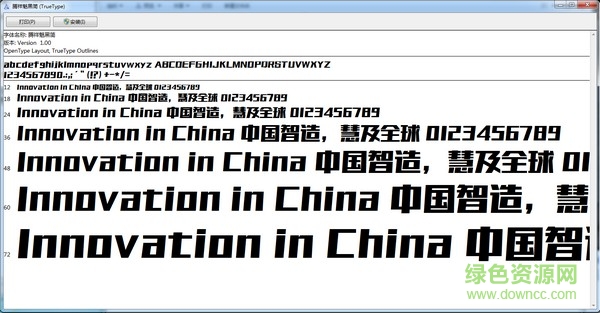
tensentype meiheij字體又叫騰祥魅黑簡(jiǎn)字體,粗而不重,布局精妙,大氣美觀,可以廣泛應(yīng)用于排版影視、包裝設(shè)計(jì)、平面設(shè)計(jì)等多個(gè)領(lǐng)域,需要的朋友快來(lái)下載吧!
魅黑是一款富于變化的美術(shù)類(lèi)黑體。魅黑是在潮黑的風(fēng)格特征基礎(chǔ)上設(shè)計(jì)而成。字形結(jié)構(gòu)扁方,橫豎筆畫(huà)粗細(xì)比例適度、所有豎筆及撇捺筆畫(huà)均呈右傾斜式,為了空間的布局,每個(gè)筆畫(huà)的傾斜角度由左至右形成梯度,使整個(gè)字看起來(lái)呈梯形,筆畫(huà)雖斜但字形穩(wěn)當(dāng)。